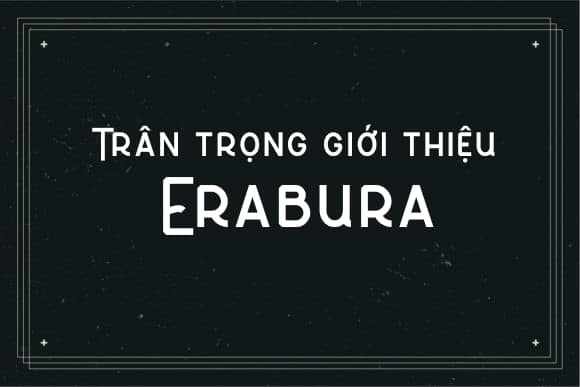
Trong thế giới thiết kế đồ họa hiện đại, việc tìm kiếm một bộ Font Chữ độc đáo và ấn tượng luôn là ưu tiên hàng đầu của các bạn học sinh và giáo viên. Font việt hoá MJ Erabura nổi lên như một sự lựa chọn hoàn hảo nhờ sự kết hợp tinh tế giữa nét chữ cổ điển và phong cách hiện đại. Đây là bộ phông chữ mang đậm tính nghệ thuật, giúp các bài thuyết trình hay báo tường trở nên sinh động và chuyên nghiệp hơn bao giờ hết.
Ưu điểm nổi bật của Font việt hoá MJ Erabura trong học tập
Độ thẩm mỹ cao và dễ dàng ứng dụng
Font việt hoá MJ Erabura sở hữu các đường nét thanh thoát, uốn lượn mềm mại nhưng vẫn giữ được sự rõ ràng cần thiết. Điều này giúp người xem dễ dàng tiếp nhận nội dung mà không gây cảm giác rối mắt. Các bạn học sinh có thể sử dụng bộ font này để làm tiêu đề bài tập lớn, thiết kế thiệp chúc mừng thầy cô hoặc làm mới các slide bài giảng thêm phần cuốn hút.
Hỗ trợ tiếng Việt trọn vẹn và chuẩn xác
Điểm cộng lớn nhất của Font việt hoá MJ Erabura chính là khả năng hiển thị tiếng Việt hoàn hảo. Mọi dấu câu, ký tự đặc biệt đều được căn chỉnh tỉ mỉ, loại bỏ hoàn toàn lỗi font chữ thường gặp. Điều này đảm bảo tính thẩm mỹ đồng nhất cho toàn bộ văn bản, giúp thông điệp truyền tải đến người đọc một cách trọn vẹn và tinh tế nhất.